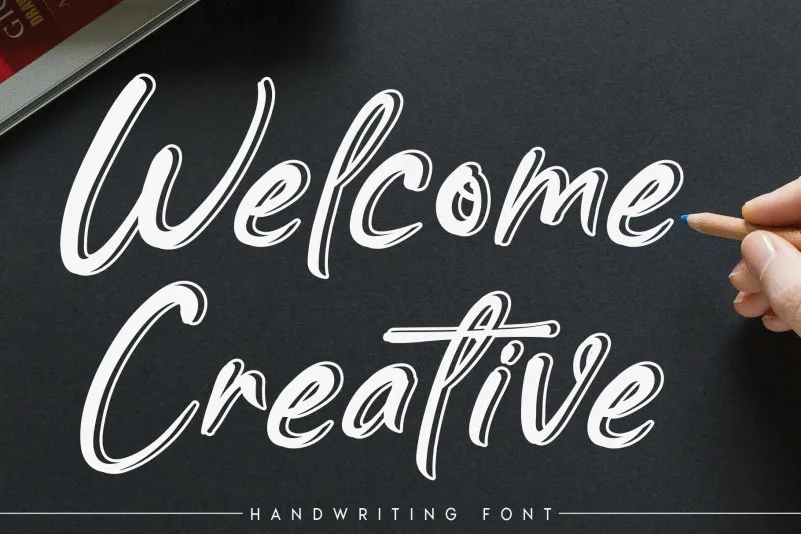
Welcome Creative Script Font – Download Grátis
A fonte ‘Welcome Creative Script Font’ é uma combinação única de elegância e casualidade que captura a essência do estilo script, criada para quem valoriza o handmade. Seu design foi inspirado na sensação de uma ferramenta de escrever delicadamente, resultando em linhas levemente fluidas e texturas distintas que conferem um toque especial à sua escrita. Perfeita tanto para uso pessoal quanto profissional, ‘Welcome Creative Script Font’ é versátil o suficiente para ser aplicada a uma variedade de ambientes. Seja você criando logotipos impecáveis para marcas, escrevendo convites de casamento elegantes, ou até mesmo desenhando rótulos personalizados – sua textura única e arredondada oferece um toque único que certamente irá chamar a atenção. A fonte também se destaca em aplicações visuais como t-shirts coloridas, cartas de boas-vindas para festivais, mensagens sobre o Instagram e até mesmo no marketing digital. Com seu design fluido e harmonioso, ‘Welcome Creative Script Font’ é uma escolha ideal para qualquer projeto que você possa imaginar.